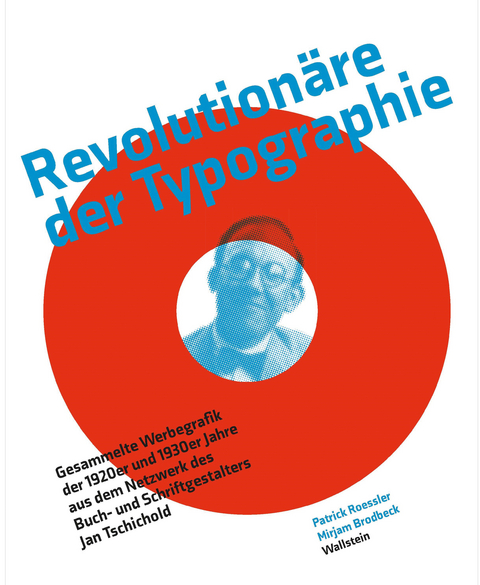
Revolutionäre der Typographie
Innerhalb eines europäischen Netzwerks der Avantgarde zusammengetragen, enthält die »Vorbilder-Sammlung« des deutsch-schweizerischen Typografen Jan Tschichold rund 1.500 kleinformatige Drucksachen. Vertreten sind berühmte Gestalter aus dem Bauhaus-Umfeld wie László Moholy-Nagy und Herbert Bayer, ebenso Künstler wie Kurt Schwitters und El Lissitzky – allesamt Pioniere des modernen Grafikdesigns.
Patrick Rössler und Mirjam Brodbeck zeigen erstmals den kompletten Bestand und präsentieren über 300 wichtige Arbeiten in großformatigen Abbildungen und zusätzlichen Erläuterungen.
Sie ermöglichen das Studium der Originale, die die Aufbruchsstimmung jener Epoche greifbar machen und die in Tschicholds Büchern meist nur in schwarz-weiß oder in stark veränderter Farbgebung abgebildet sind.
So weitet sich der Blick auf ein Netzwerk von 45 Gestaltern und auf ein Kapitel der europäischen Avantgarde, das den »Swiss Style« der Nachkriegszeit unmittelbar beeinflusste.
Jan Tschichold (1902-1974) gehört zu den bedeutendsten Designern der Moderne und gilt als Vorreiter des funktionalen Grafikdesigns, der sogenannten Neuen Typographie. Seine persönliche Kollektion mit typografischen Muster.beispielen aus der Zwischenkriegszeit, die er in seinem Unterricht wie in seinen Veröffentlichungen einsetzte, übergab er schon 1936 dauerhaft der Schule für Gestaltung Basel, an der er seinerzeit lehrte.